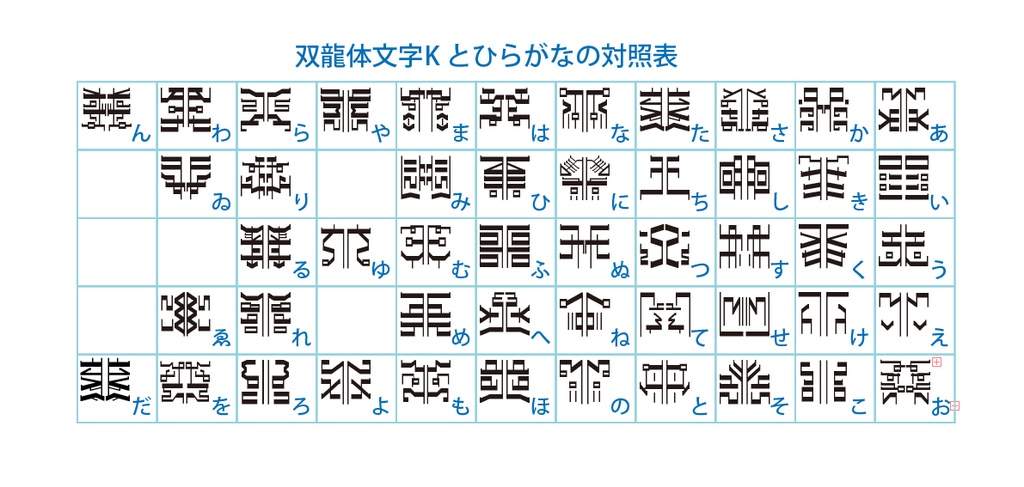
デジタルコンテンツ 双龍体文字Kフォント
双龍体文字のオリジナルフォントです。 龍体文字とは神代文字の中でも最も古く5600年前に作られたと言われる文字。48字ある文字それぞれにパワーが宿っているとされています。その龍体文字を鏡合わせにした合成文字が双龍体文字です。 ひらがな48文字(ゐゑ含む)に対応した龍体文字があるので、ひらがなを入力すると相当する龍体文字が表示されるようにしました。 フォントファイルの形式はOpenTypeファイルです。 MacOS SequoiaとWindows11での動作確認はしています。 【収録文字】 ひらがな(あいうえおかきくけこさしすせそたちつてとなにぬねのはひふへほまみむめもやゆよらりるれろわゐゑをん) ※濁音、半濁音、拗音、促音はありません。 ※「た」の龍体文字の書き方には2とおりあるようなので、異体字を「だ」に収録しました。 【データ内容・使用方法】 zipファイルを解凍してください。 OpenTypeファイル pksoryutaik-Regular.otf JPGファイル(龍体文字とひらがなの対照表) comparison.jpg テキストファイル readme.txt が収録されています。 pksoryutaik-Regular.otfをインストールしてください。 【購入の際の注意点】 商用利用OKです。 使用した場合、ご一報いただけるとうれしいです。X(旧Twitter)などで紹介します。 フォントファイルの改変・再配布は禁止です。